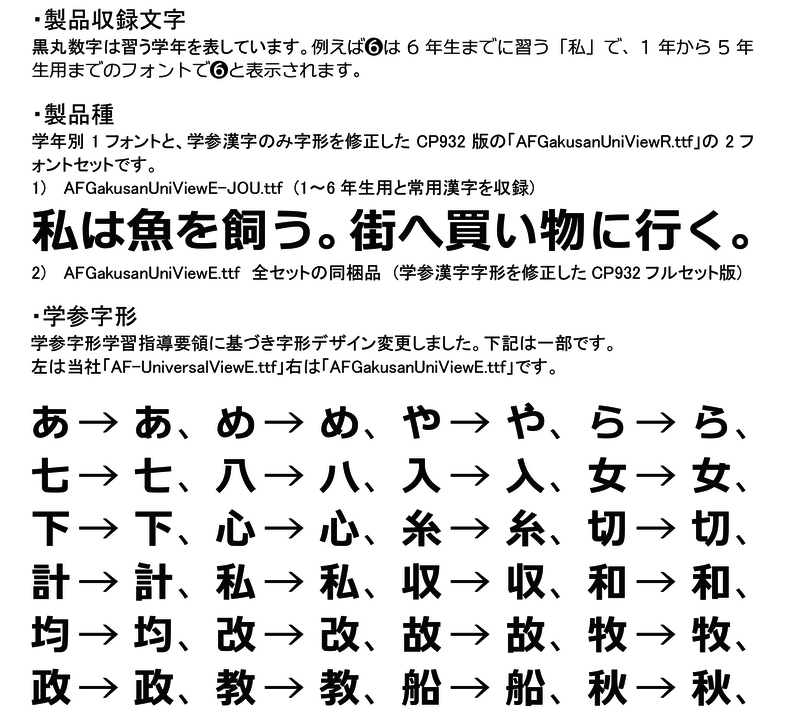
可読性を重視したユニバーサルビューのレギュラーをベースに文部科学省学習指導要領の字形を再現。ドリル等教材用はもちろん児童を対象とした配布資料作成に最適です。1年から6年までに学習する学参文字と常用漢字を収録したフォントと学参漢字のみ字形を修正したCP932フルセット版の2書体セットです。AFGakusanUniViewE-JOU.ttf
学参 常用E